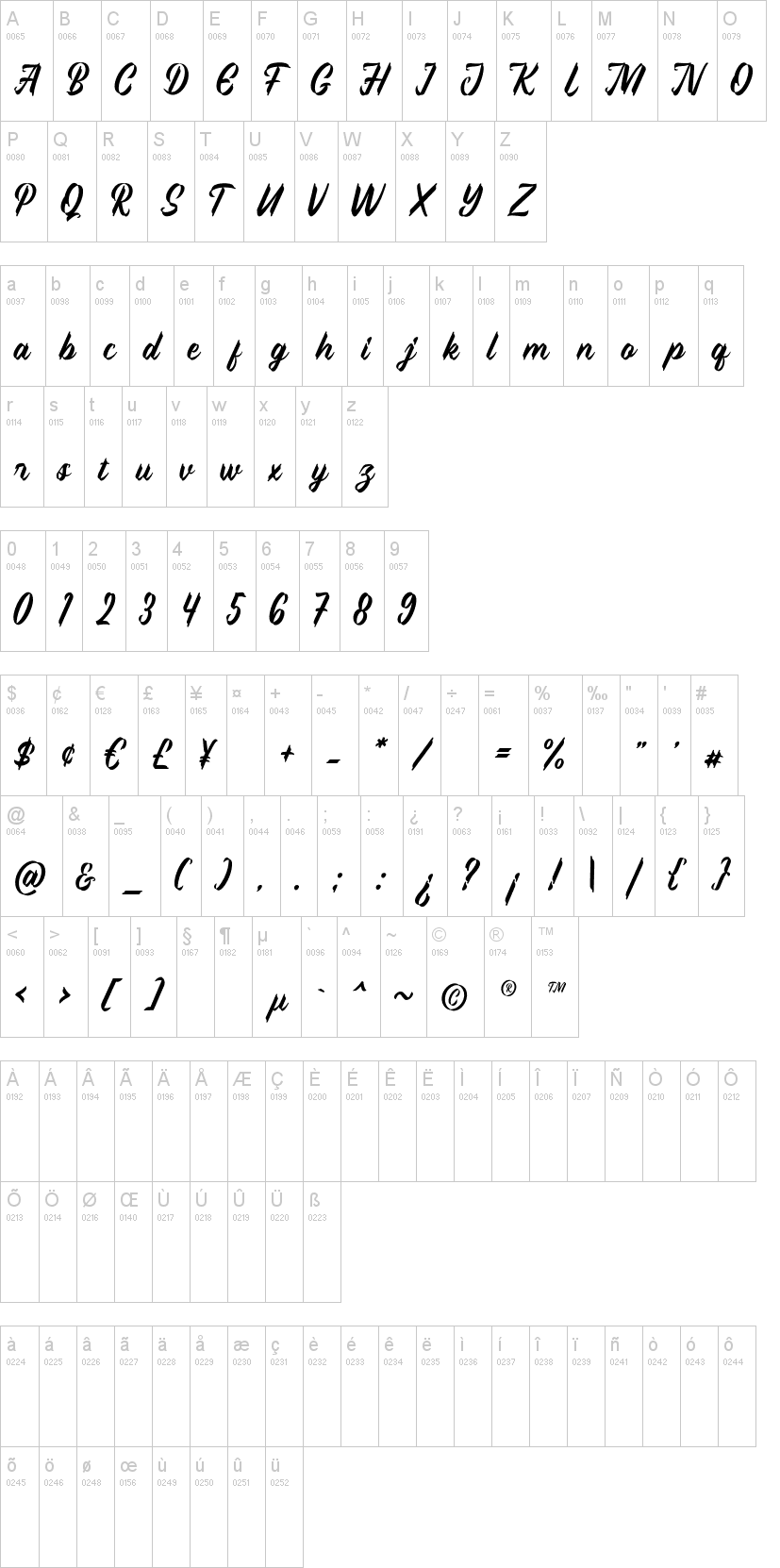
Sweet Pancake
Sweet Pancake是一款设计师GemFonts在2019年发布的欧美风格字体,它拥有清新优雅的设计,可以为您的作品带来清新的气息。它具有轻松柔和的线条,拥有清新、时尚、优雅的特点,适用于海报、书籍、网页等设计。它的符号和字体也拥有清新的外观,可以更好地表达您的想法。
Sweet Pancake是一款非常不错的手写艺术字体,具有很好的视觉感,适合于文化类的宣传设计、商业类品牌的广告和产品包装设计以及个性化文字排版等较多场景。
Sweet Pancake字符映射图